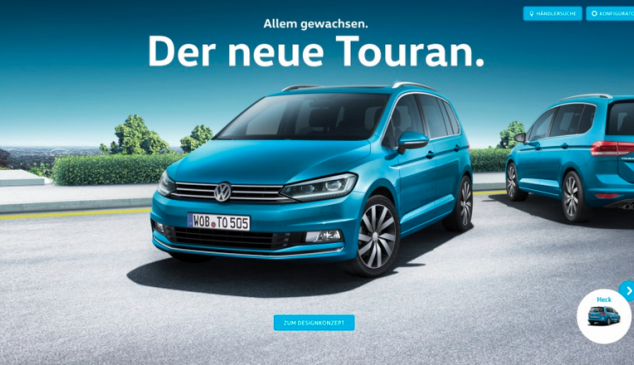
Volkswagen renueva su tipografía
La marca automovilística ha rediseñado su tipografía de la mano del tipógrafo Hannes von Düren de MetaDesign, la misma consultora alemana que se ha encargado de los diseños de Volkswagen desde 1997.
La razón que ha llevado a la marca a rediseñar su identidad tipográfica ha sido que “el diseño de la cabina es cada vez más digital. Eso significa que los elementos de la marca, como el tipo de letra, van siendo más prominentes dentro de los vehículos”.
Además, según han comentado desde Volkswagen, el uso de un tipo de letra que sea propiedad de la marca acabará siendo más rentable. Y es que esta decisión supone que la compañía se ahorrará los pagos por derechos y licencias de uso.
Xavier Chardon, jefe de marketing de Volkswagen Brand Cars ha afirmado que "tener un tipo de letra que podemos utilizar tanto en nuestra comunicación como en nuestros productos es una nueva calidad para Volkswagen. Este tipo de letra está obviamente inspirado en nuestro diseño de los vehículos y, con él, se comunica el carácter de nuestra marca ofreciendo a los clientes una experiencia de marca Volkswagen distinta y sostenible”.
El nuevo diseño
El objetivo ha sido crear una tipografía que se basara en el “respeto a las normas técnicas modernas y a criterios tales como el espacio, la legibilidad, el multilingüismo y la viabilidad cross-media”.
En la anterior imagen se presenta el antiguo diseño (izquierda) frente al nuevo (derecha)
El resultado ha sido un diseño que “irradia dinamismo, modernidad y un toque humano”, según han explicado desde MetaDesign.
La consultora se ha declarado satisfecha con el nuevo tipo de letra. De hecho, considera que "como en el diseño distintivo de los vehículos Volkswagen, la forma y la función armonizan para crear un todo unificado. Los ángulos, las aristas y las curvas crean puentes visuales y un flujo agradable".